IG手寫字體下載|38款中文手寫字體全攻略
你也想在 IG 限動中使用手寫字體嗎?有別於 IG 系統內建幾乎毫無變化的字體,你也可以使用手寫字體讓限動增加獨特溫暖與個性。本篇將整理 38 款熱門中文手寫字體下載資源,並且延伸介紹爆紅的線上手寫字型產生器,讓你輕鬆找到屬於自己的手寫風格!
一、手寫字體的應用與情境:找到適合你的手寫字風格
(一)使用手寫字體設計版面有什麼好處?
手寫字不同於制式的印刷字體,每個人寫出來的筆觸風格、粗細、力道等,都能展現作者的個人特色,因為近幾年自媒體、個人品牌盛行,大家也更喜歡在 IG 限動、Reels 或 Youtube 影片中使用不同風格的手寫字體,讓社群內容更豐富有人性、引人注目,呈現出截然不同的感覺。
溫度感:讓作品和內容更有人味與故事性
獨特性:不易被複製,凸顯個人或品牌特色
設計感:靈活搭配插畫、照片,提升風格層次
(二)常見手寫字體風格有哪些?
溫暖可愛風:圓潤飽滿,適合社群貼文、影片與插畫作品
優雅古典風:筆畫帶有古典或硬筆字優雅韻味,適合內容製作
隨性率性風:不拘小節的個人筆觸,給人輕鬆隨意的感覺
每個人的手寫字體其實都有不同的風格和特色,所以只要搭配上合適的畫面和情感,就能傳達獨一無二的畫面囉!接下來讓我們一起來看看有哪些可以使用的手寫字體吧!
二、手寫字體資源整理:38款手寫字體介紹與下載
想知道有哪些免費與付費的手寫字體可以使用在 IG 限動或社群貼文嗎?我們整理出熱門的 38 款字體介紹與字體下載點,讓你能找到最適合你的手寫字體!
(一)20款免費手寫字體下載
辰宇落雁體
辰宇落雁體已經是一款眾所皆知的手寫字體,因為他柔美且流暢細膩的筆觸,讓文字更增添了詩意和美感,是各種設計作品中常見的免費商用手寫字體首選。
小賴字體
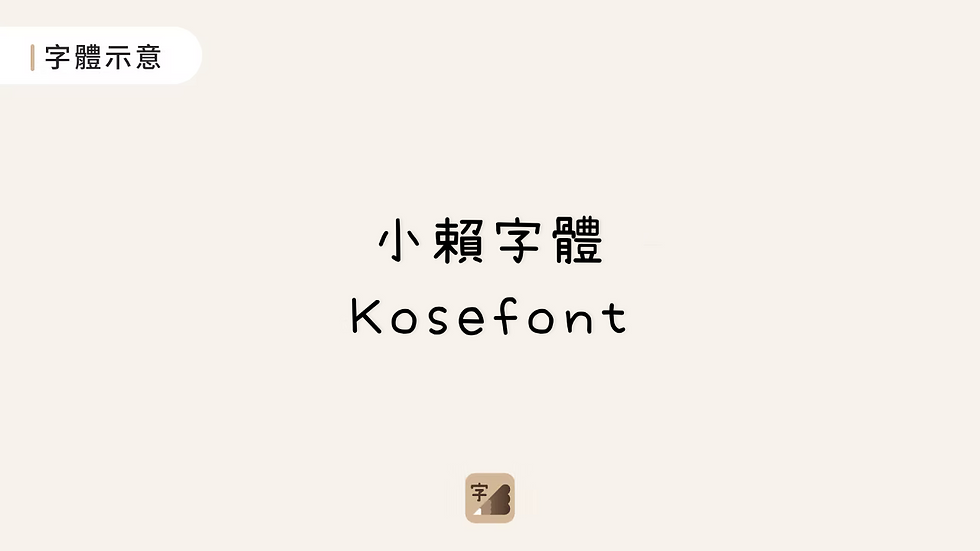
小賴字體是由日本的瀨戶字體再補上更多漢字,手寫風格獨特又可愛,因此在設計、社群排版等各種視覺內容時,都能增添一份溫暖可愛的氣息。
瀨戶字體
瀨戶字體是由日本設計師精心打造,其獨特的手寫風格和可愛的筆觸,深受大眾喜愛。這款字體不僅支援日文,更涵蓋了繁體中文和簡體中文,使其在設計海報、文書等各種視覺作品時,都能增添一份溫暖可愛的氣息。
內海字體
內海字體和小賴字體一樣,也是從瀨戶字體衍生而來的一款字體,除了新增豐富的中文字和特別的標點符號外,更提供 5 種字重,滿足不同設計需求。
清松手寫體
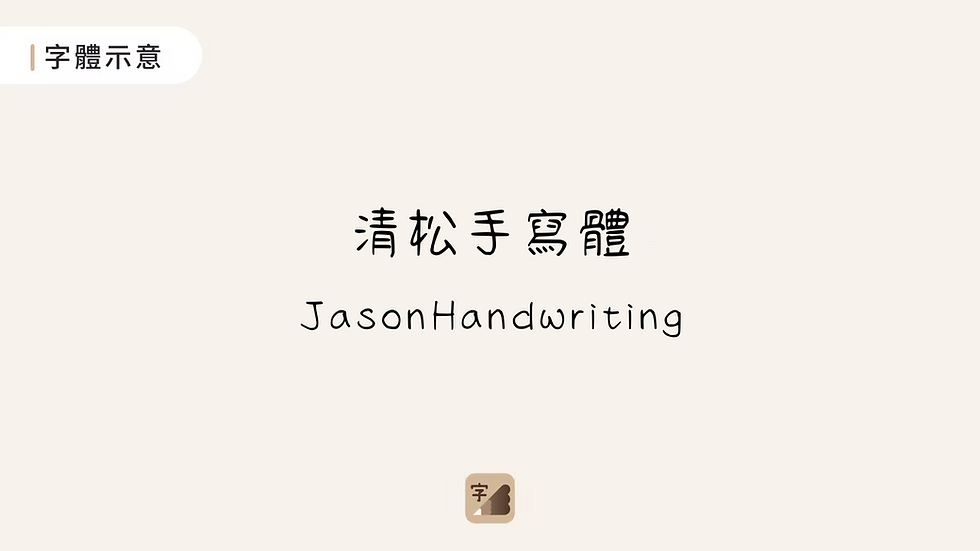
清松手寫體是一款持續更新中,且個人與企業都能完全免費使用的手寫字體,目前共釋出 8 套不同風格的清松手寫體,包含圓潤、秀氣、呆萌、POP、行楷、Q萌、飄逸、隨性。
芫荽字體
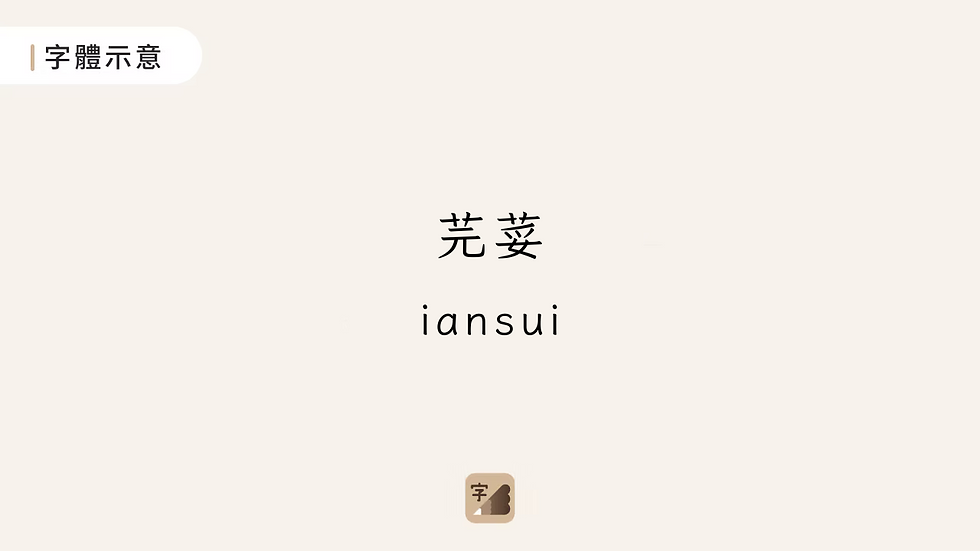
芫荽是由日文字體 Klee 改作,保留楷體和仿宋的筆調,並且調整至貼近教育部標準字體,也有台客語用字,是第一套為台灣教育所用的字體,硬筆書寫的風格符合現代書寫習慣,優雅易讀。
何某手寫體
何某手寫體是由日文字體 おつとめフォント 改作,筆畫有粗細變化,帶有直白、樸素的手寫感,並且有 5 種不同字重,是一款可以免費商用的字體。
星空小熊貓體
由白河寫字運銷合作社透過「手寫字型產生器」創作的星空小熊貓體,帶有孩子般童趣稚氣的風格,是一款可愛的手寫字體。
壱城ラウラ字體
壱城ラウラ字體(壱城ラウラフォント),風格筆觸很自然隨性,潦草中又帶有一點可愛,收錄字數超過 2 萬字,而且是一款可以免費商用的手寫字體。
851 手寫體
851手寫體是一款日文字體,但字數高達3萬多字因此中文字也幾乎不缺字,筆畫帶有日常手寫的連筆感,很適合日常類型的內容。
宅在家自動筆
由巴哈創作者「天天宅在家」製作的手寫字體,字型結構方正中帶有稚氣感,帶有手寫時的自然感與細微的不規則,視覺上有種扁扁的感覺。整體帶有樸實、親切的氛圍,適合用在日常筆記、生活感內容的分享。另有兩款宅在家手寫字型,分別是「宅在家麥克筆」、「宅在家粉條甜」,一樣提供免費商用。
曉聲通秋茄體
曉聲通秋茄體是一款帶有正楷、硬筆風格的手寫體,筆畫清晰易讀。筆形符合國語教學《教師手冊》標準,字體內容多元,包含閩南語、客家話、日本語及港澳用字,並支援注音、拼音、雙拼注音三種版本。
苦累蛙圓體
苦累蛙圓體是紅道字體的補字計畫,調整部件寫法、新增中文字、增加5個字重、增加一些符號。是一款帶有圓珠筆的手寫風格,有著獨特的字體骨感之美。
莫大毛筆字體
莫大毛筆字體改編自日本書法家青柳衡山的衡山毛筆字體,彌補繁體中文的缺字遺憾。字體偏向書法瘦金體,以飛白多、墨量少為特色。
Musin 無心體
Musin 無心體是個令人感到有點慵懶、有點可愛的手寫字型,適合當作裝飾字使用。由於本身是日文字體,因此使用於繁體中文時較容易缺字。
快去寫作業字體(CEF Fonts CJK)
「快去寫作業字體」是一套完全使用滑鼠繪製的「仿」手寫體。適合運用在書籍、插畫、影片等藝術創作。
たぬき油性マジック
日本超商常見的手寫宣傳海報的字體總令人印象深刻,這樣的手寫溫度在「たぬき油性マジック」字體中實現了!帶有油性麥克筆手寫字體風格,使用上非常有特色!由於本身是日文字體,因此使用於繁體中文時較容易缺字。
菊體
下筆App 裡面有一款「 菊體 」其實是市面上看不到的字體,因為它是 2017 年底,由筆闆媽媽一筆一劃親手寫下的,一直到 2022 年下筆誕生之後,菊體自然也成為內建的一款字體,菊體就像家人親切的問候和關心,我們也很開心能把媽媽的這份溫柔變成美好生活的一部分。
漢儀新蒂浪花體
漢儀新蒂浪花體的線條非常細膩,筆畫中帶有海浪動態感,適合文青分享日常。
新蒂西瓜體
圓潤中帶點直線的俐落筆畫,在視覺上形成獨特的對比。